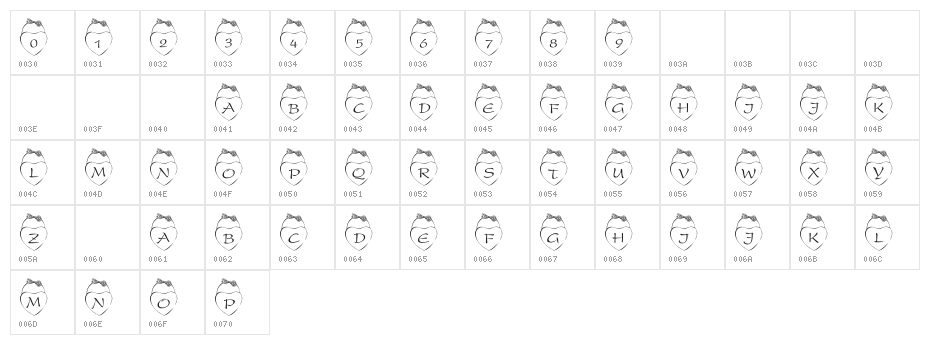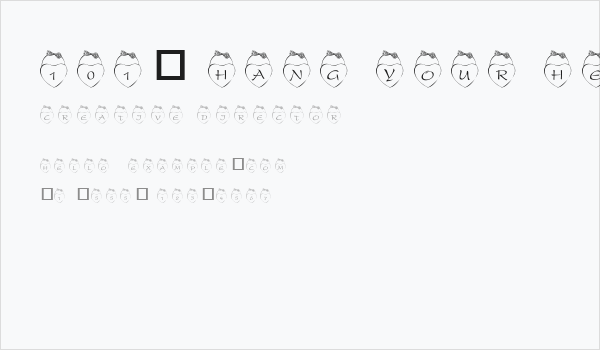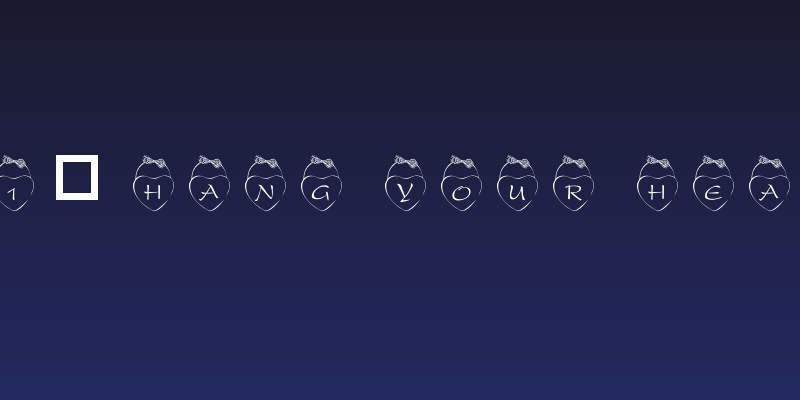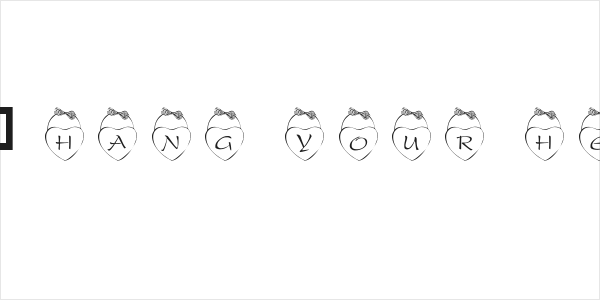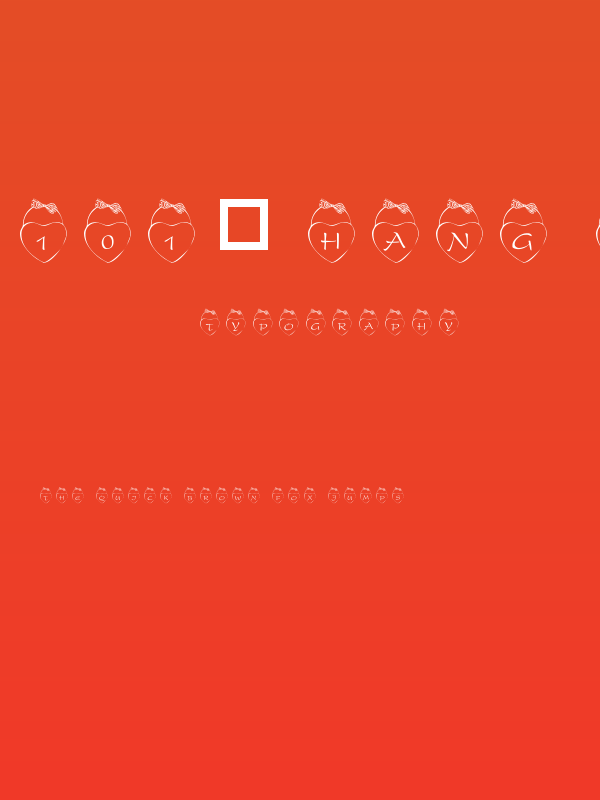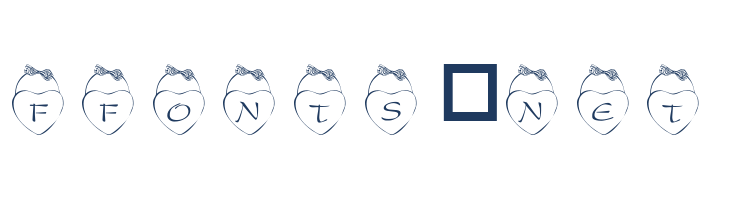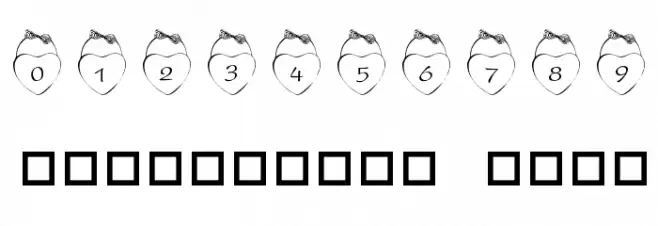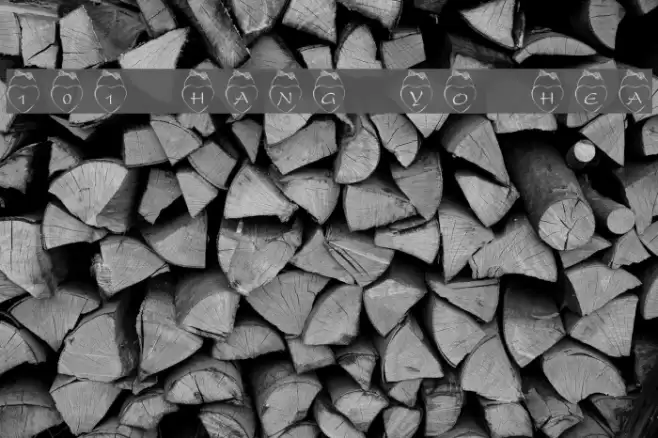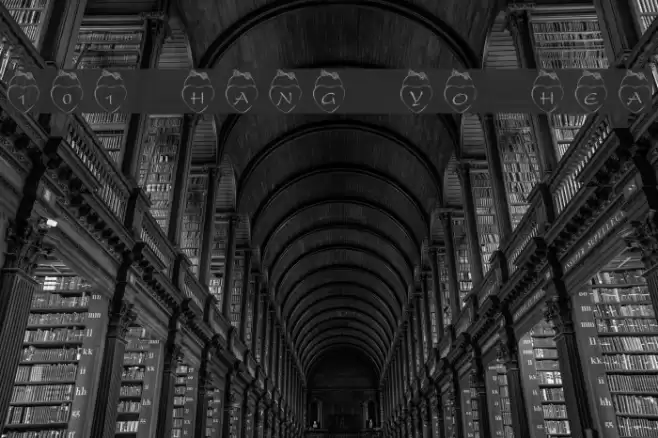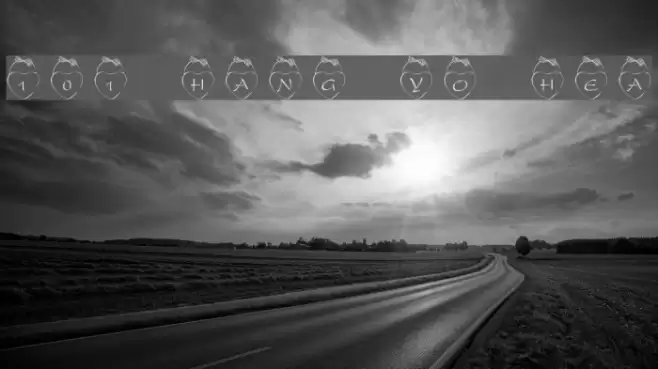
101! Hang Your Heart Font
✎ Valentine
| Cas d'utilisation | Logos, Invitations, Themed Events |
| Projets proposés | Ideal for wedding invitations, Valentine's Day cards, romantic event branding, and playful children's designs. |